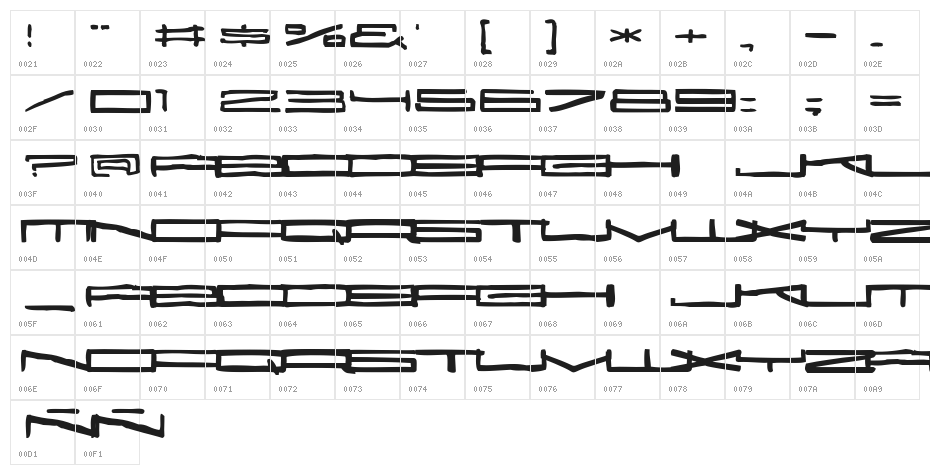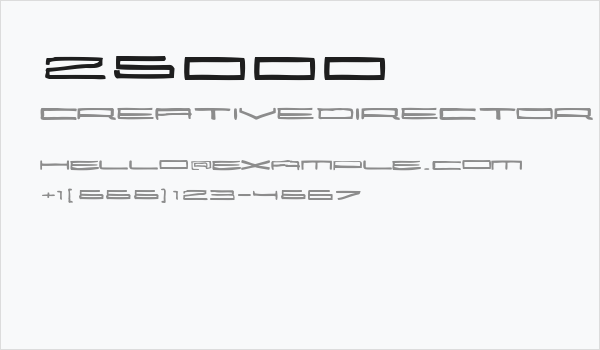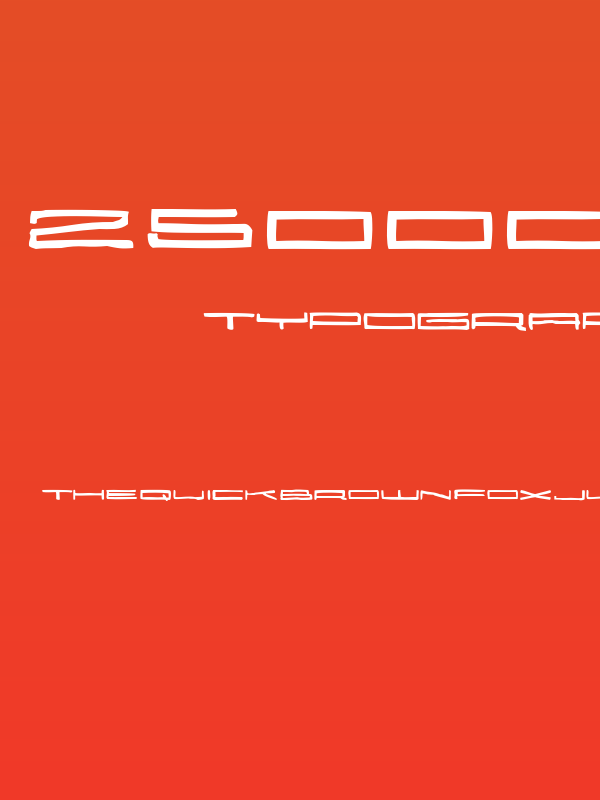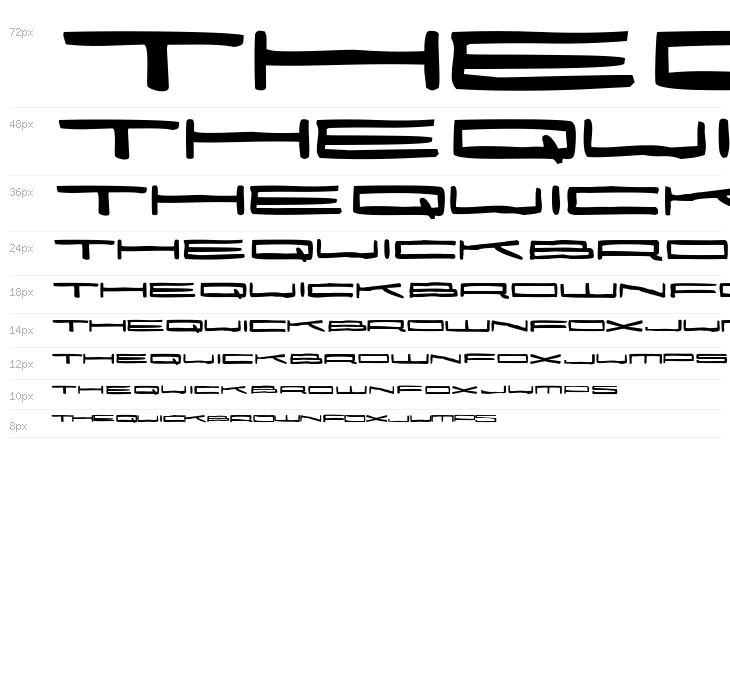
25000 Font
✎ Distorted Eroded
| Vorgeschlagene Projekte | Ideal for technology branding, sci-fi themed graphics, innovative product packaging, and modern web design. |